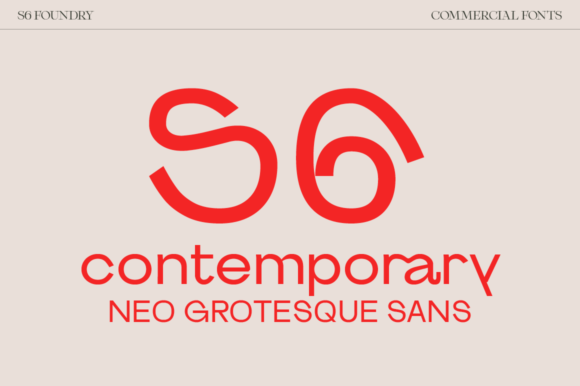
[Creativefabrica] S6 Sans Font
S6 Sans - это минимальный и аккуратный шрифт без засечек.
Его легко подогнать под невероятно большой набор проектов, так что добавьте его к вашим творческим идеям и заметьте, как он выделяет их на фоне других!